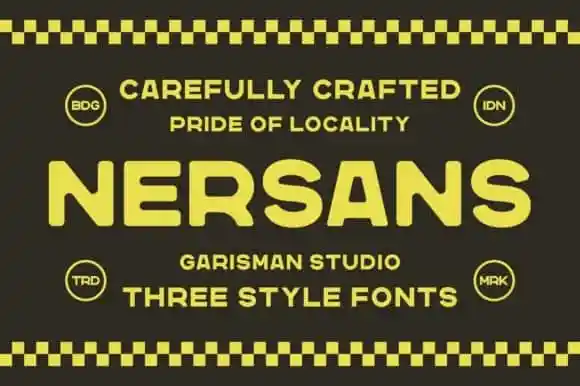
A Nersans Sans Serif Font é uma novidade na categoria de tipo sem serif que se destaca por sua extra condensação e estilo unicase, criando um efeito único e moderno para projetos digitais. Desenvolvida pelo designer Garisman Studio, essa fonte leva os usuários a tempos nostálgicos sem perder seu carácter atual e sofisticado. Seu design vintage e retro cria uma atmosfera autêntica que permite aos designers criar ideias de design memoráveis com um toque de nostalgia inigualável. A Nersans Sans Serif é perfeita para quem busca trazer a vibe dos anos 50 ou 60 em qualquer projeto visual, seja em cartazes, letras de músicas, títulos de apresentações ou até mesmo pequenos detalhes nas redes sociais. Este tipo de fonte sem serif, extra condensada e com unicase é perfeito para quem valoriza o passado enquanto mantém um olhar no futuro.